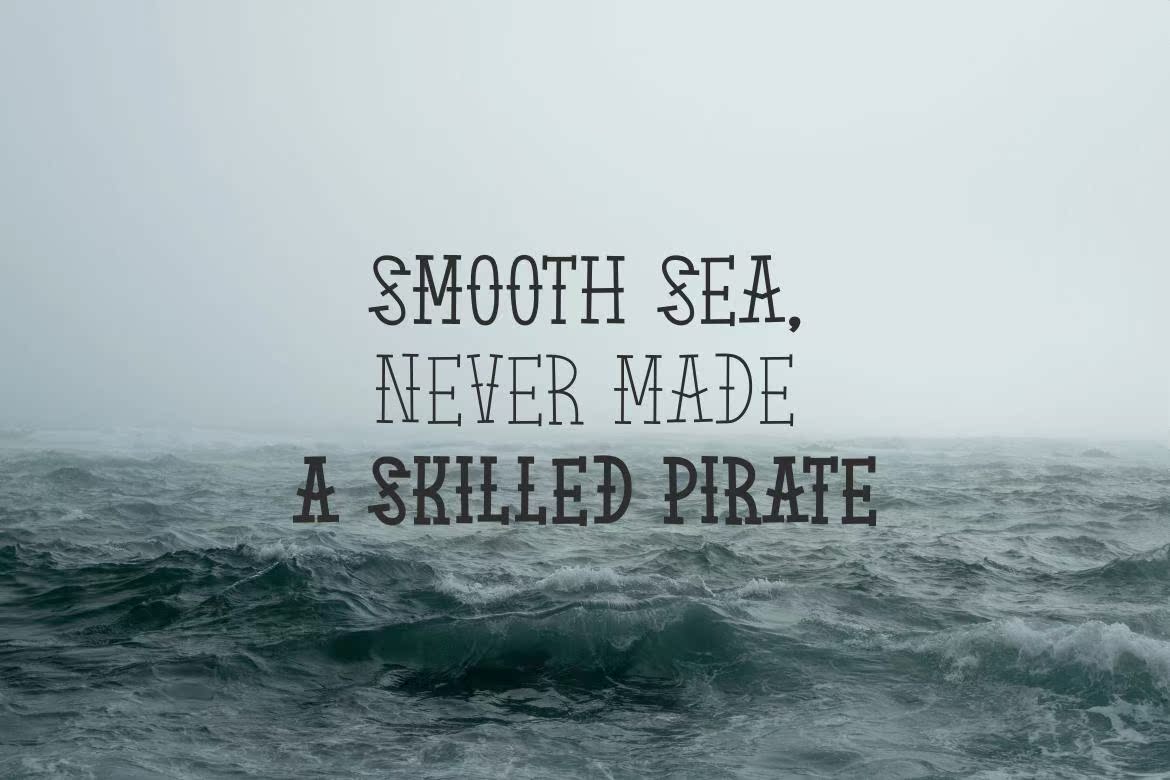
3(三)重、规则、粗体和黑色的AnalCapsFont。具有干净的金色纹身样式、一磅重和大量刺激。Elbiratosis是RoughFontrographysea的队长。3(三)重、规则、粗体和黑色的AnalCapsFont。具有干净的金色纹身样式、一磅重和大量刺激。Elbiratosis是RoughFontrographysea的队长。